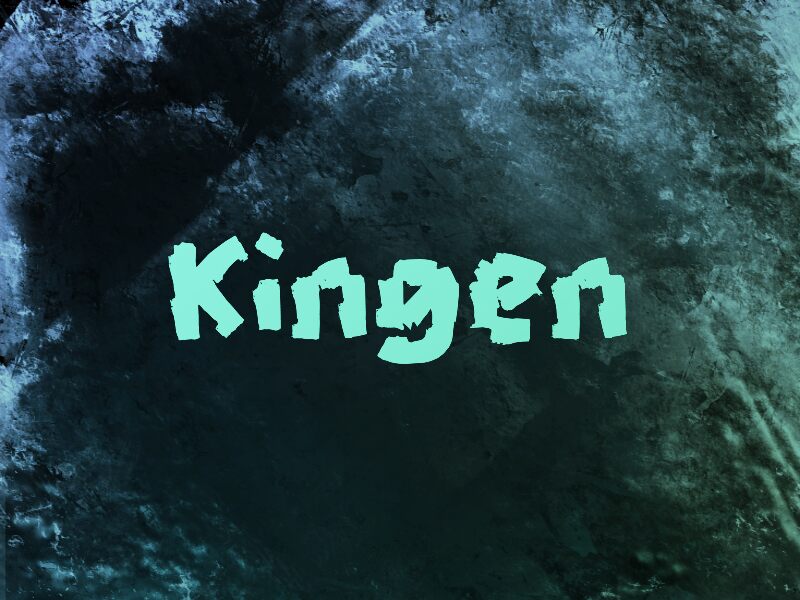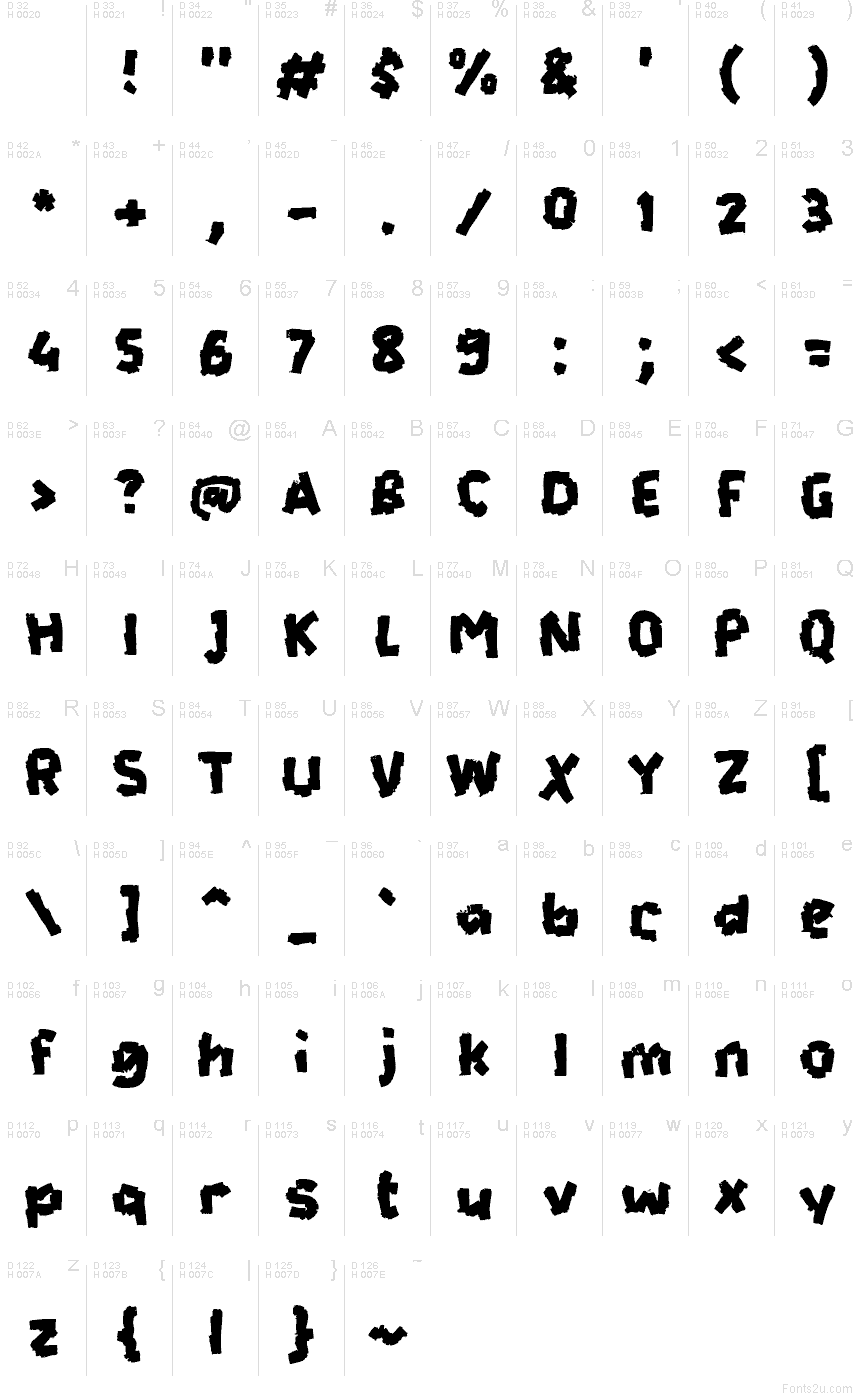
Kingen
Kingen od Wep je bezplatné display písmo s drsným rezom, tvarované ako útržky čierneho papiera stlačené do podoby písmen. Zúbkované vonkajšie okraje a tupé, nepravidelné bloky dodávajú písmu rytmus ručného výrezu, ktorý pôsobí skôr ako koláž než ako ťah štetcom alebo opotrebovaný efekt.
Vďaka tomu je Kingen silnou voľbou pre názvy plagátov, obaly albumov, ziny, hororovú grafiku a pozvánky na akcie, kde surová silueta zaváži viac než uhladenosť. Krátke nadpisy, grafika na merch a bannery na sociálne siete tiež ťažia z tejto „poskladanej“ textúry, ktorá dáva každému slovu výraznú, nalepenú prítomnosť namiesto neutrálneho dojmu.